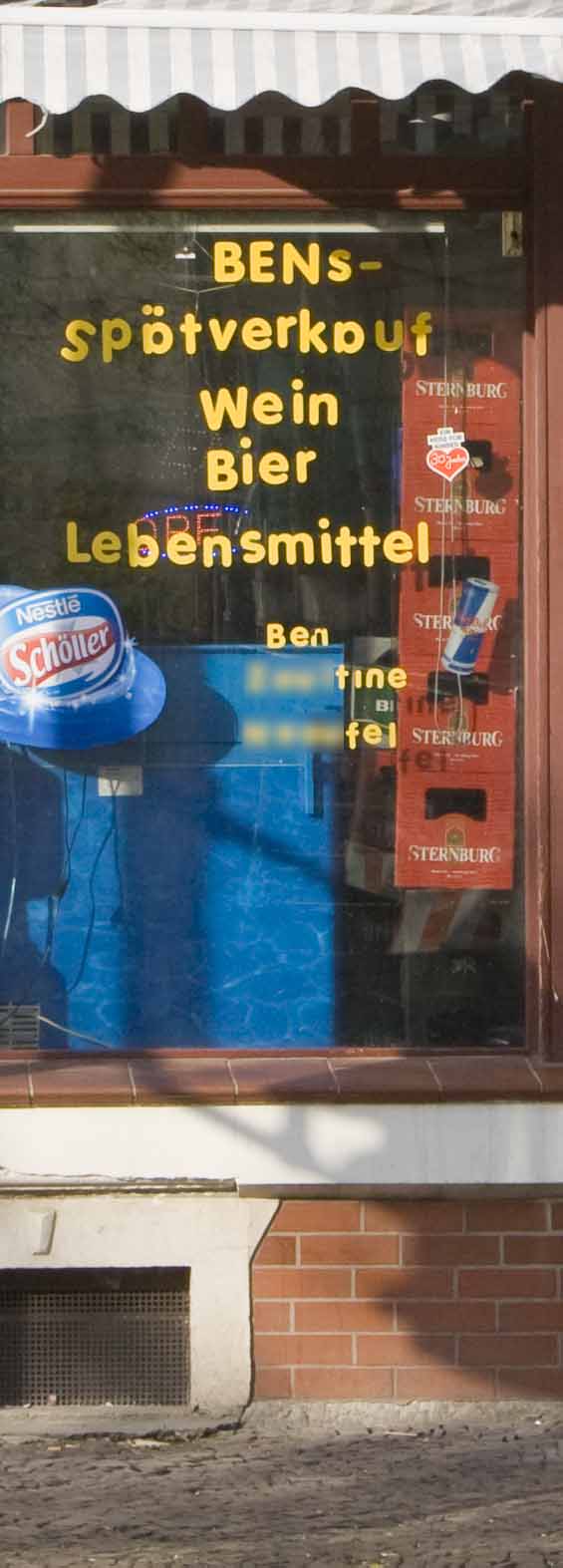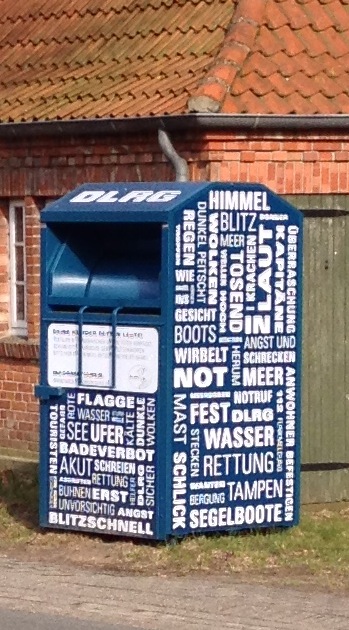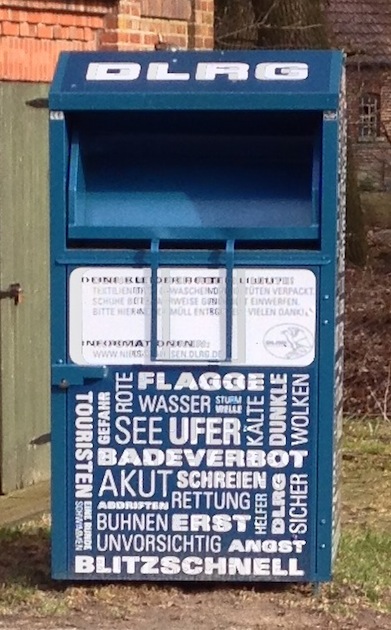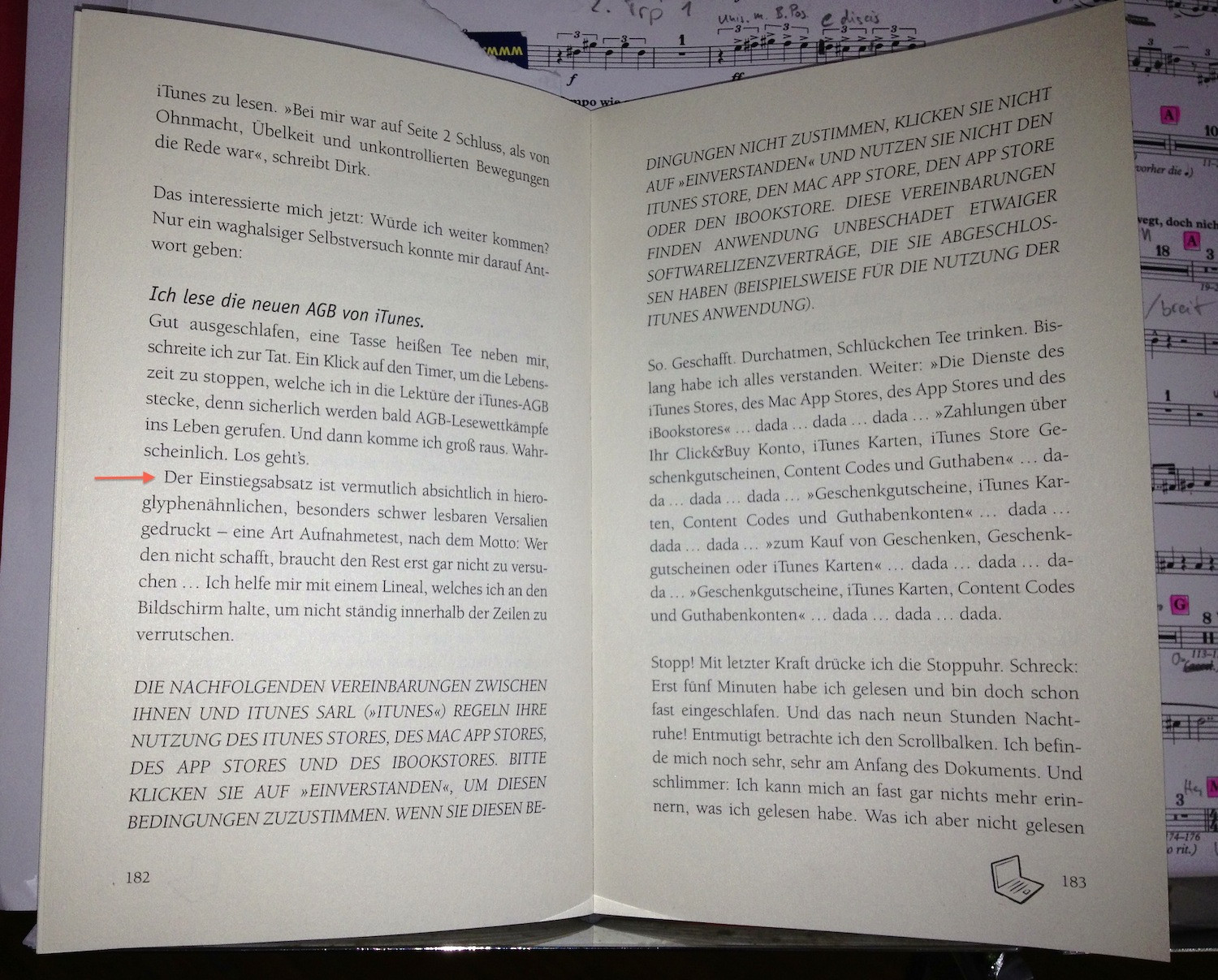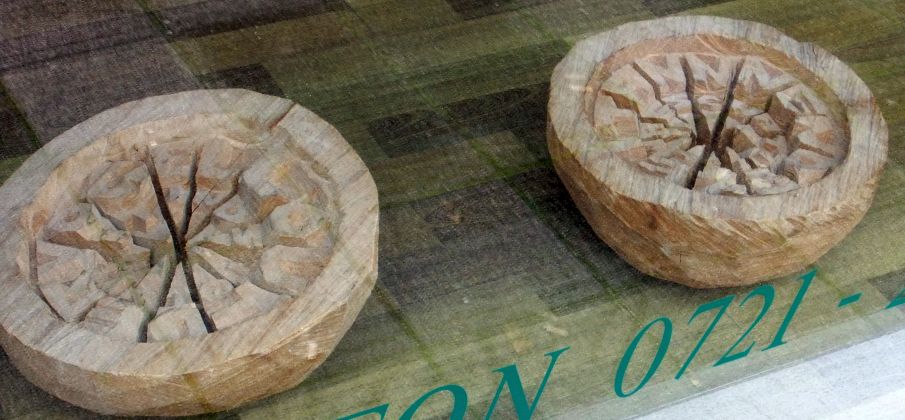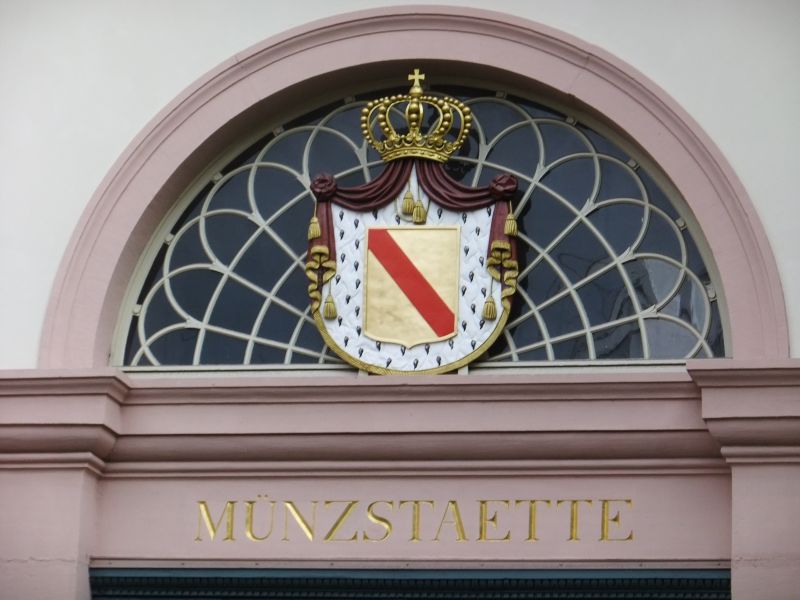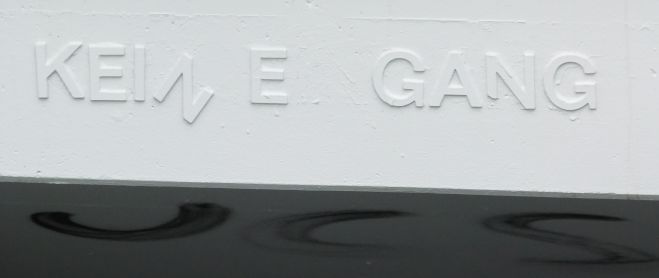
Gutenberg hat keine Blackletter Schriften erfunden, sondern bewegliche Lettern.
Nö, bewegliche Lettern gab es schon lange vor Gutenberg, u. a. in weiten Teilen Asiens. Er gilt als Erfinder des Handgießinstruments und der Druckerpresse.
Buchstabenlampen
Gibt es aber scheinbar (noch) nicht zu kaufen …
Speziell diese Buchstabenlampen vielleicht nicht, aber beispielsweise urbansigns verkauft filetierte Leuchtreklame buchstabenweise: http://urbansigns.ch
Selbst basteln wäre auch noch eine Option. Einer der Antiquitätenhändler auf meinem Weg hat grad ein mannshohes E zum Verkauf aus einer ehemaligen Leuchtreklame.
aktuelle Ausgabe einer Zeitschrift für Buddhismus
Erkennbar sind Elemente der Stoa, des Daoismus und des Buddhismus, da Vernunft und Selbstbeherrschung statt Leidenschaft und Begierde betont werden ...
Auch das Element des Erlösers, das sich neben dem Christentum auch im Mahayana-Buddhismus und anderen Religionen findet, ist vorhanden: Anakin Skywalker ist „der Auserwählte, der die Macht in das Gleichgewicht bringen soll.“ Ein Messias, der eine bessere Welt schaffen soll.
Aufträge ...
"Achso?! Ich hätte die Kugeln außen beschriften sollen?"
"Im Auftrag stand nur 'alles frisch grau streichen'!"
MU...
"Du, ich glaube, das wird irgendwie zu breit?!"
"Dann mach halt Punkte über U und A!"
MÜNZSTA...
"Du, ich glaube, das wird irgendwie doch zu schmal?!"
"Dann erinner Dich an den Auftrag: AE!"
Aus »Drücken Sie bitte die Eins« Willkommen in der Servicehölle:
Und ein Altkleidersammelcontainer aus Osterfeine: